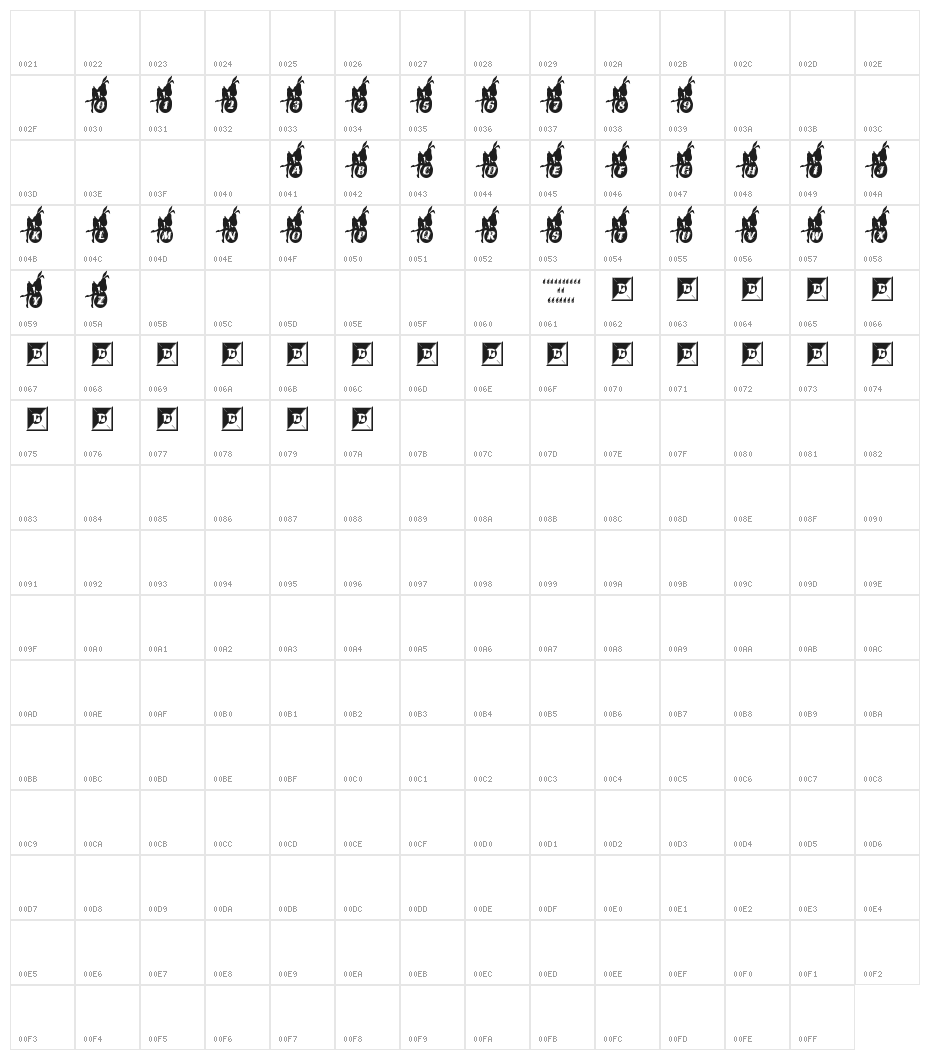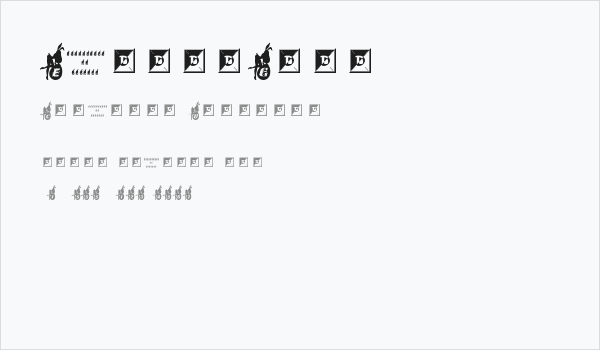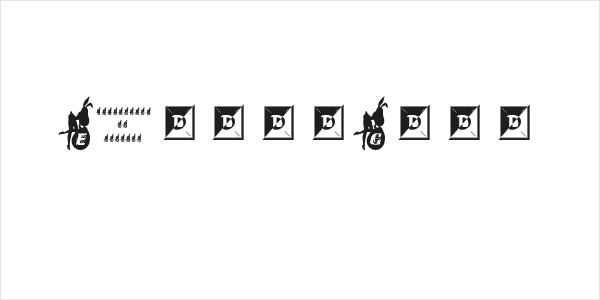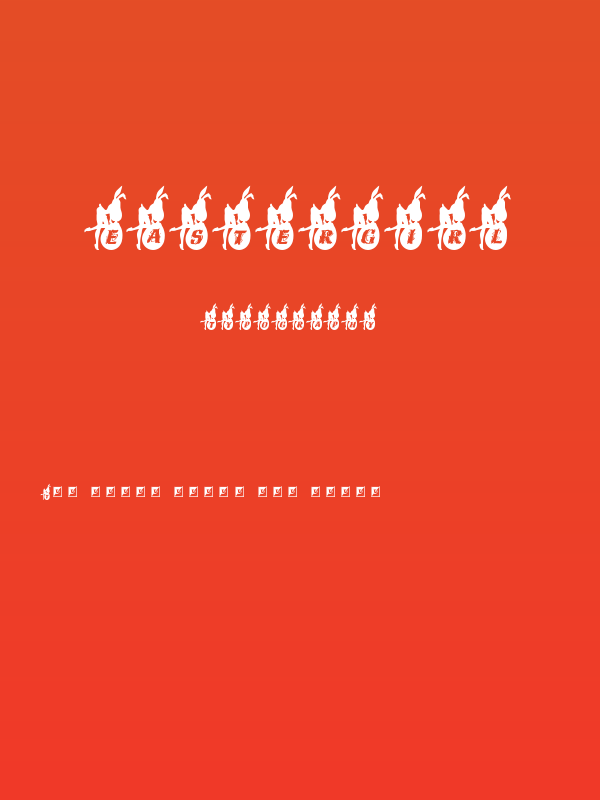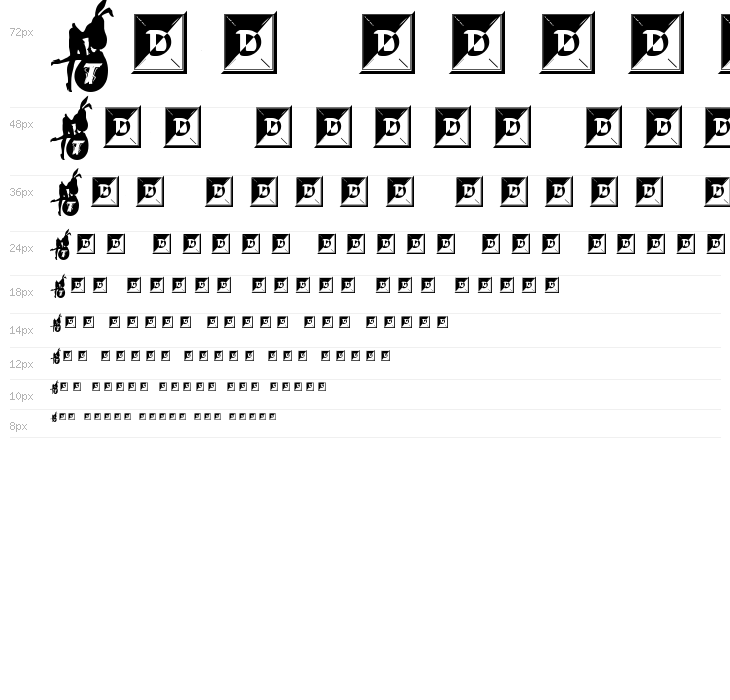
EasterGirl Font
| Vorgeschlagene Projekte | Ideal for Easter-themed designs, children's book covers, playful event invitations, and decorative logos. |